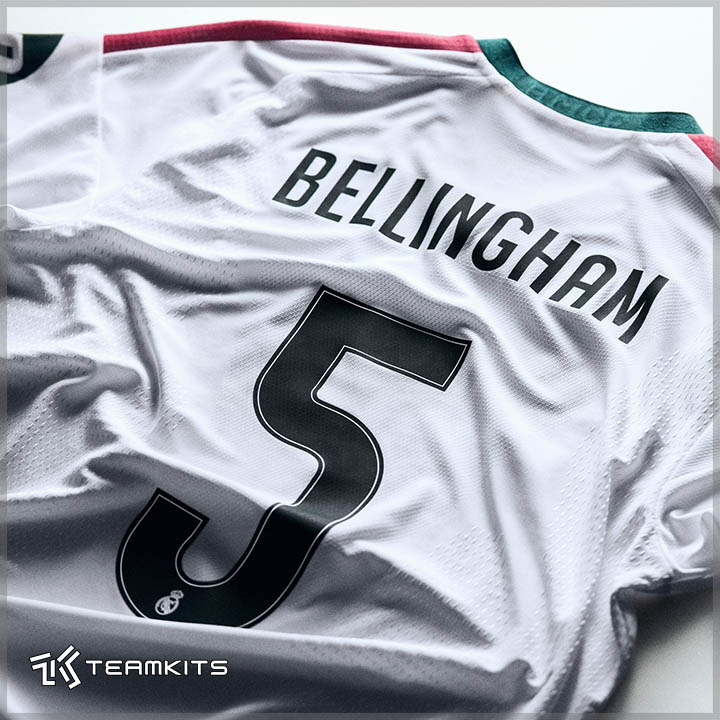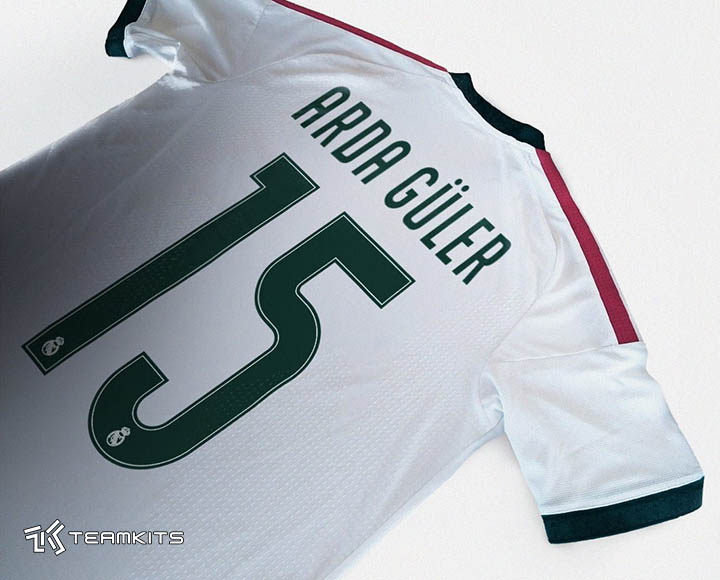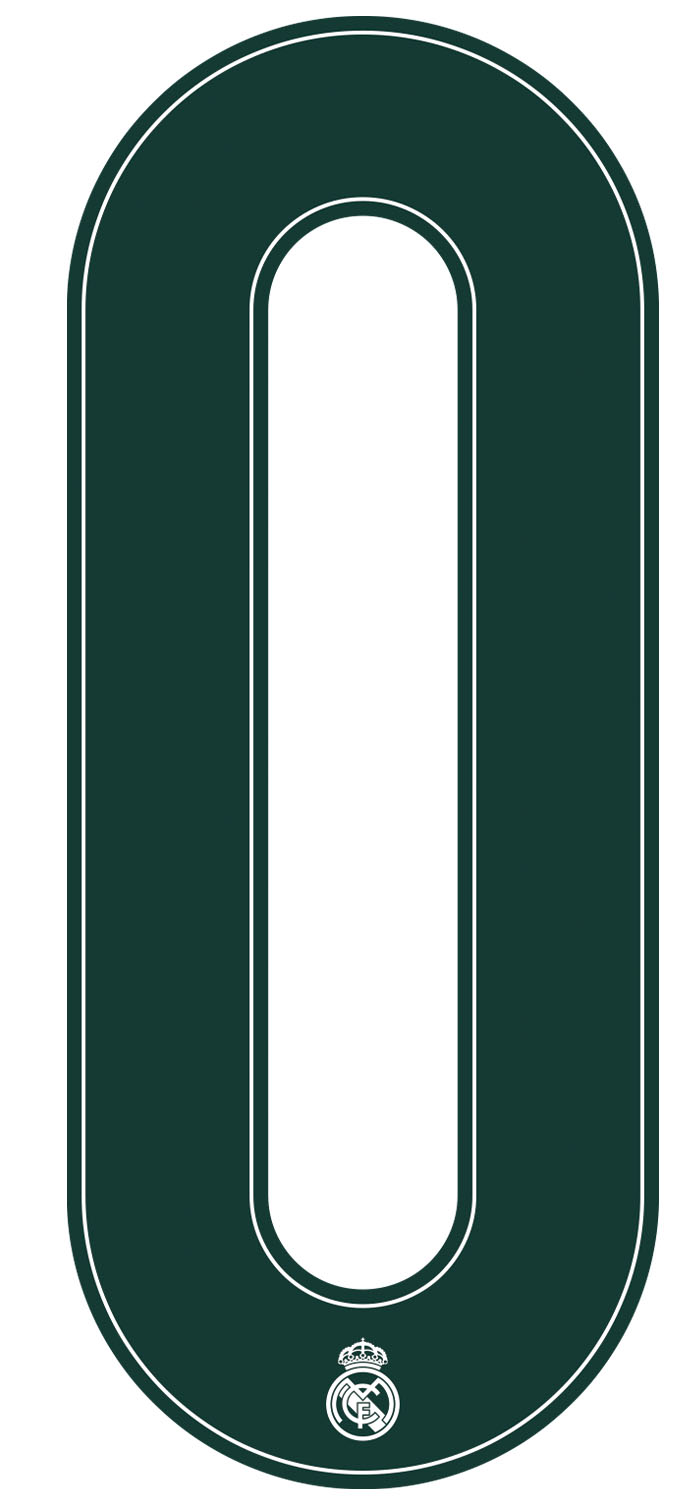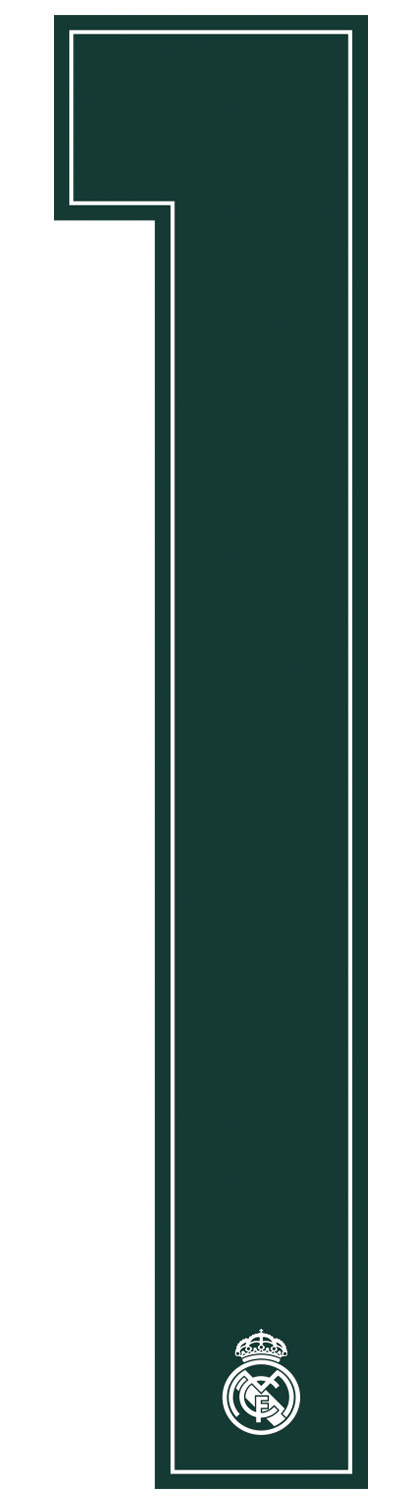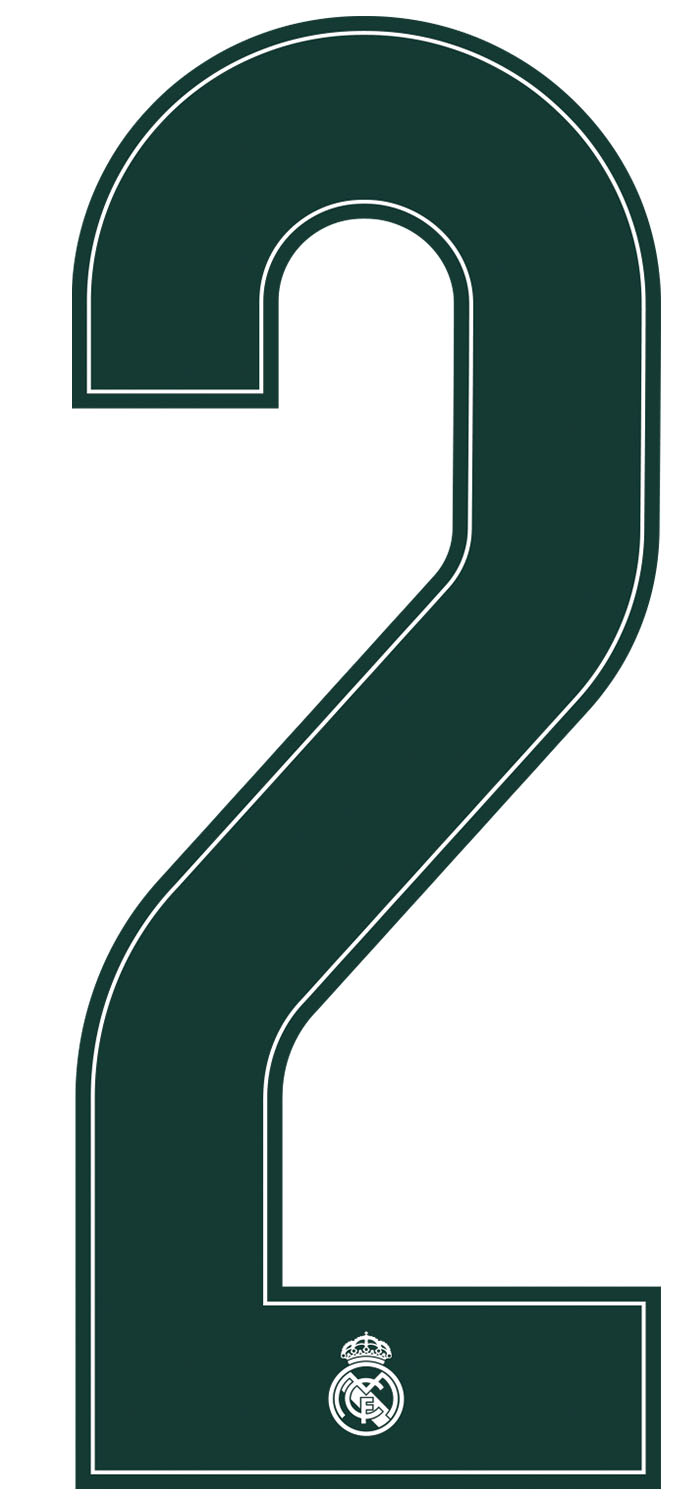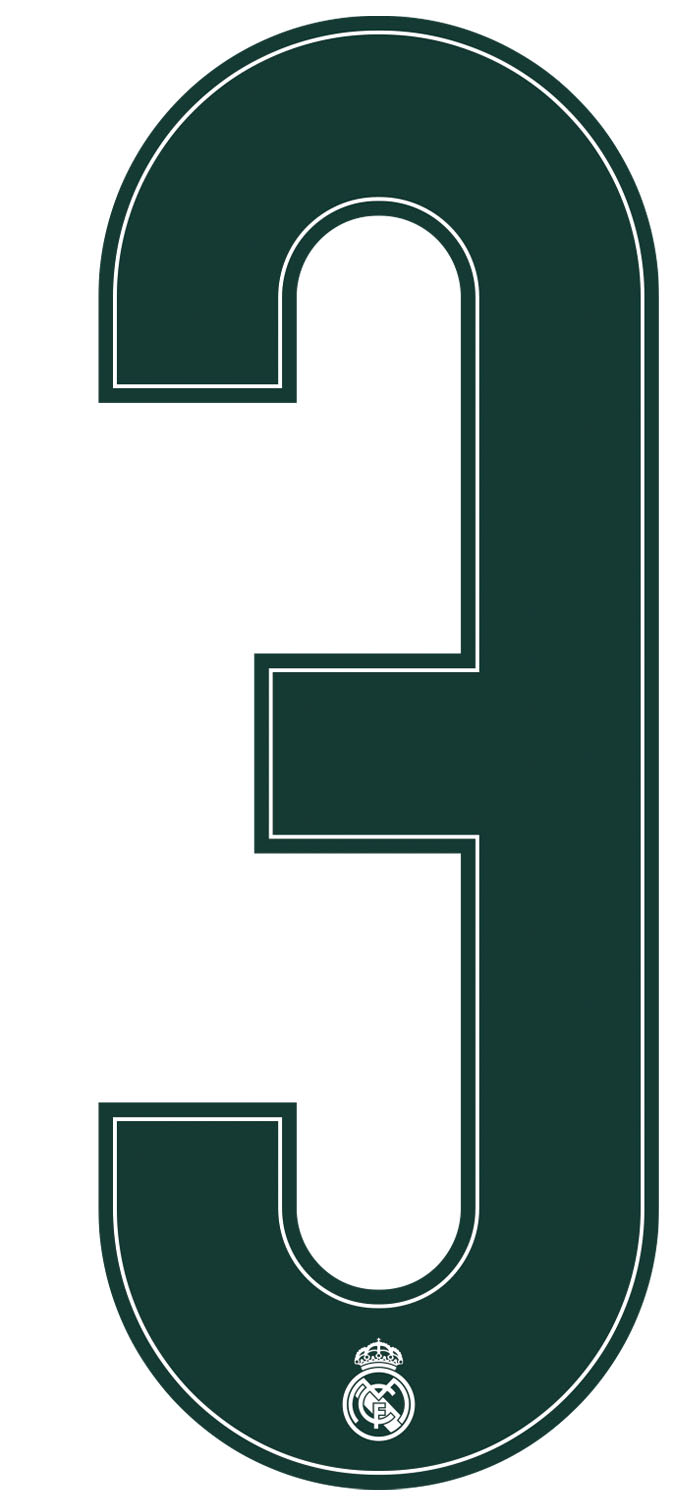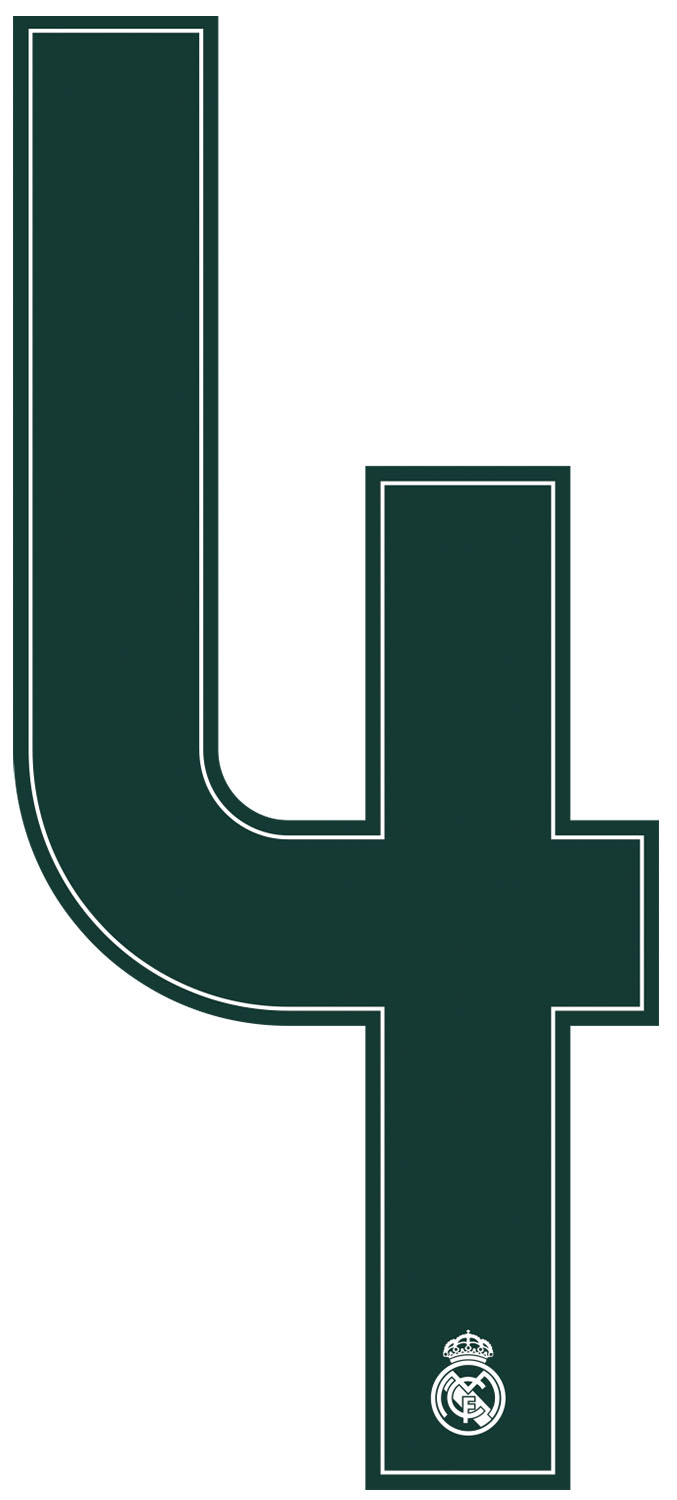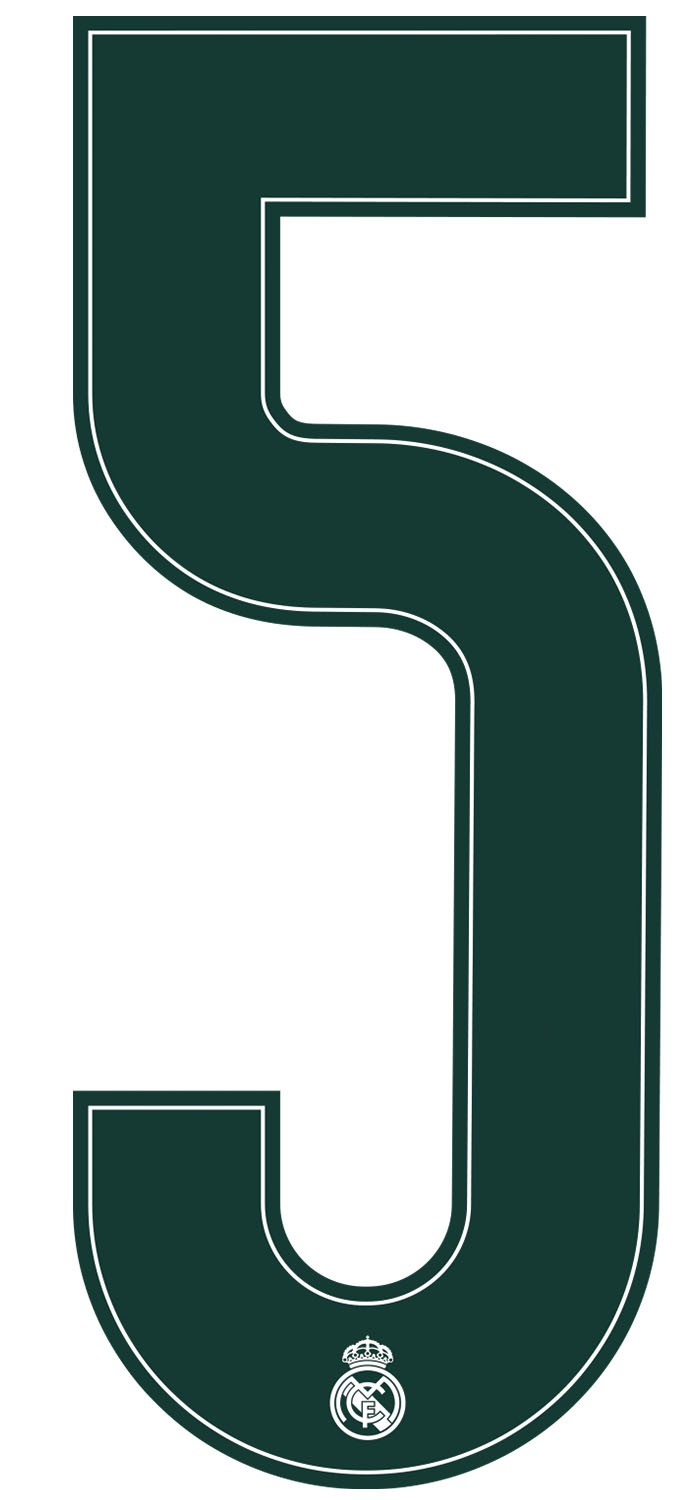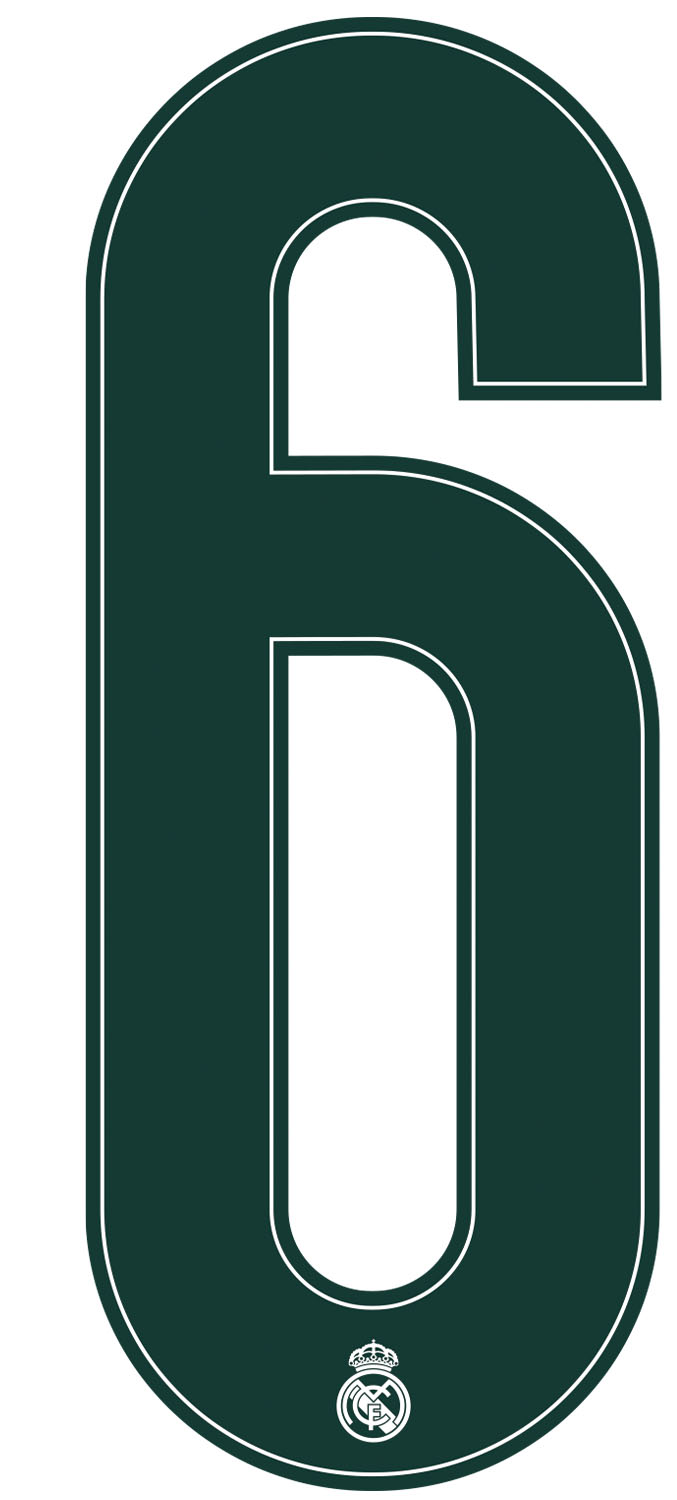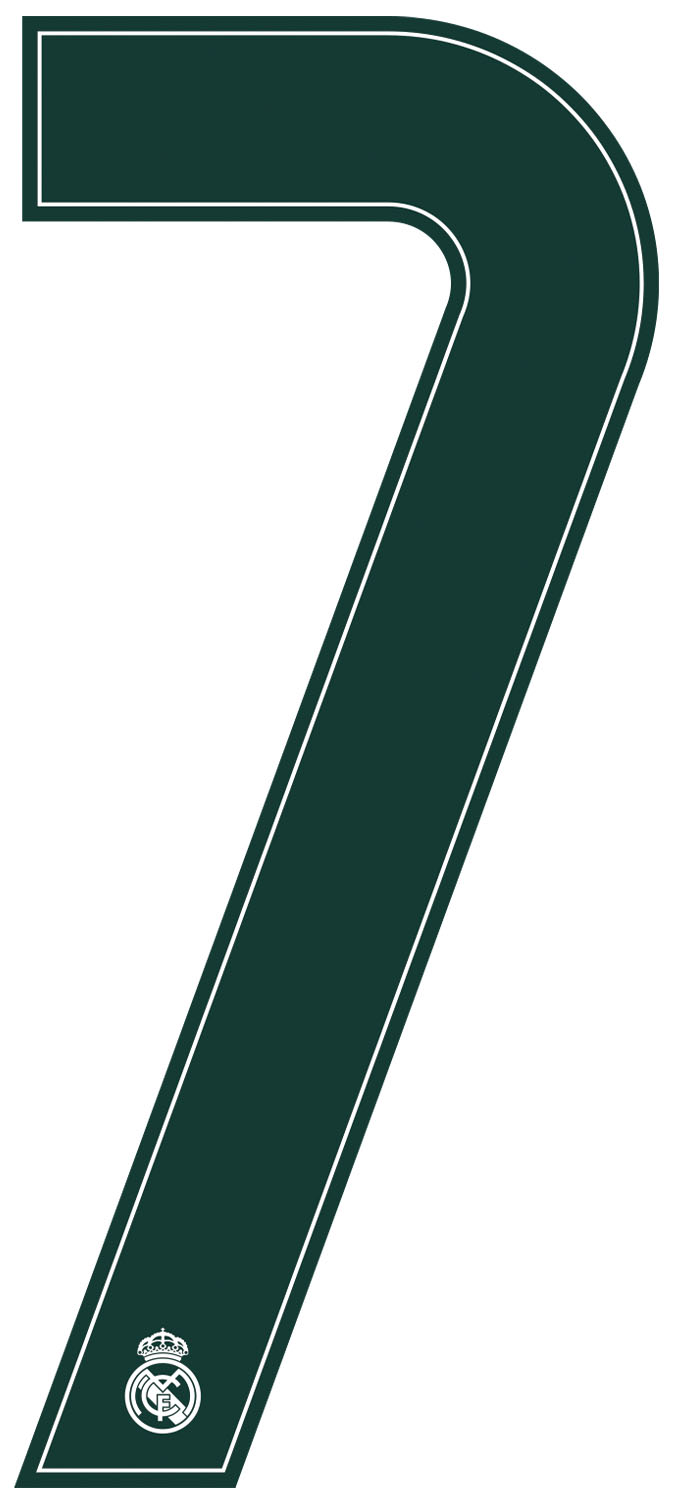
تیم کیتز – فونت رسمی نام و شماره رئال مادرید در فصل ۲۰۲۷-۲۰۲۶ همزمان با عرضه لباس اول جدید این تیم عرضه شد.
فونت جدید با ساختار استاندارد و ضخامت نسبتا کم، از فرم کشیده و تا حدودی نرم بهره می برد. قالب کلی اعداد مستطیل بیضی ایستاده و حروف نیز از همین قالب تبعیت می کنند.